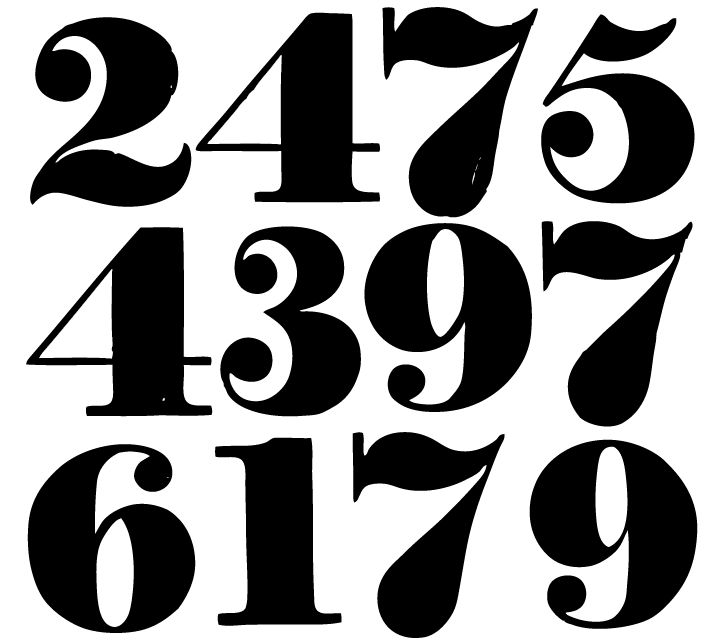
Красивые шрифты, символы, буквы для оформления имён, ников, профилей.
Красивые и крутые символы — набор значков, букв, закорючек и смайликов для оформления различных текстовых кусочков или отдельных слов. Принцип оформления текста, основан на замене стандартных букв необычными символами, которые напоминают по форме исходные. Второй способ, симметричное добавление по краям текста красивых символов.
Наиболее популярными элементами для оформления сейчас являются: ники для игр, псевдонимы, имена для соцсетей, статусы, профили Instagram, описания каналов Telegram или Tiktok. В дополнение, некоторые пользователи используют красивые символы на аватарках или фотографиях.
Онлайн шрифты для текста, надписей, ников и статусов.
Красивые цифры для ников. Разные онлайн шрифты цифр для оформления текстов, имён, никнеймов, профилей.
Красивые цифры и шрифты для них используют в профилях и постах Instagram, оформлении видео роликов TikTok, группах VK и каналах Telegram.
Для цифр есть примерно 6 разновидностей шрифтов, этого достаточно, чтобы украсить любой текст или сообщение. Если вы любите автоматизацию, используйте формы для быстрой генерации красивых текстов.
Шрифт Zennadoo
Zennadoo — это креативный шрифт с заглавными буквами, доведенный до совершенства. Отличный выбор, если вы ищете числа и цифры с немного большим влиянием, чем обычно!
Шрифт для пишущей машинки
Typewriter — это классический шрифт для механической пишущей машинки, доступный в обычном и полужирном начертании, идеально подходящий для старых документов, писем и эффектов ретро-дизайна.